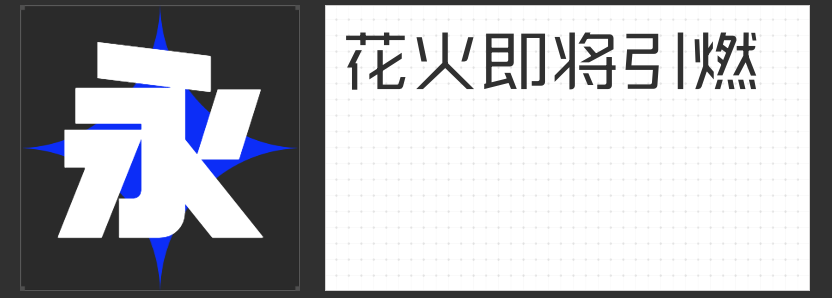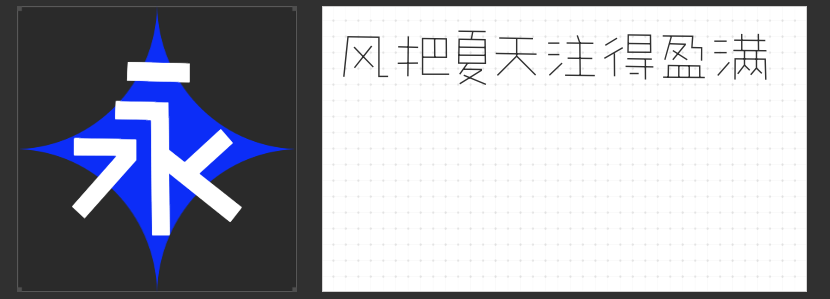
探索可变字体的魅力:四款推荐
在字体设计的世界里,可变字体以其独特性和灵活性受到了广泛的关注。今天要为大家推荐四款令人印象深刻的可变字体。
首先,让我们来看看“励字造梦简可变字体”。这款字体以其左侧倾斜右侧竖直的不对称设计脱颖而出,夸张的透视感仿佛让人置身于繁华的城市之中,抬头仰望那些摩天大厦。直线型的字体设计赋予了它力量感,棱角分明的字形轮廓清晰有力,让人一眼就能感受到它所传递的坚定与执着。
接下来是“励字可变志向黑简”。这款字体巧妙地将圆体与黑体融合,通过增加适当的外圆角,使得整体字形在稳重大气中又不失灵动。其字面充实、结构稳定,非常适配屏显使用,无论是在手机、电脑还是其他电子设备上,都能展现出极佳的视觉效果。
再来看看“励字勇敢黑简可变字体”。这款字体没有衬线装饰,笔划粗壮有力,撇捺等笔画不尖,使得它非常易于阅读。横直均匀的笔划设计让它更加突出醒目,常用于标题、导语和标志等场合。它的设计简洁大方,又不失力量感,是许多设计师的心头好。
最后,我们来了解一下“字恋狂可变漫野”。这款字体以手写感为基础,结构张弛有度,布白空间通透。不同字型之间有细微的大小变化,大小错落的设计使得版面更加活跃。笔画设计简洁而不呆板,钩笔画、弯钩笔画进行了去钩处理,部分笔画还运用了“断开”的特点,使得整体字体更加富有节奏感。
这四款可变字体各具特色,无论是用于标题、正文还是标志设计,都能展现出独特的魅力和视觉效果。它们不仅丰富了我们的设计选择,更为我们的创作提供了更多的灵感和可能性。如果你正在寻找一款独特且富有表现力的字体,不妨试试这四款可变字体吧!